Calligraphy fonts: Tổng hợp các font chữ thư pháp đẹp nhất
Trong bài viết hôm nay, xin chia sẻ đến các bạn tổng hợp các font chữ thư pháp hiện đại (calligraphy fonts) đẹp nhất. Mời các bạn cùng tham khảo nhé!
Love Rosnita font (Envato Elements)
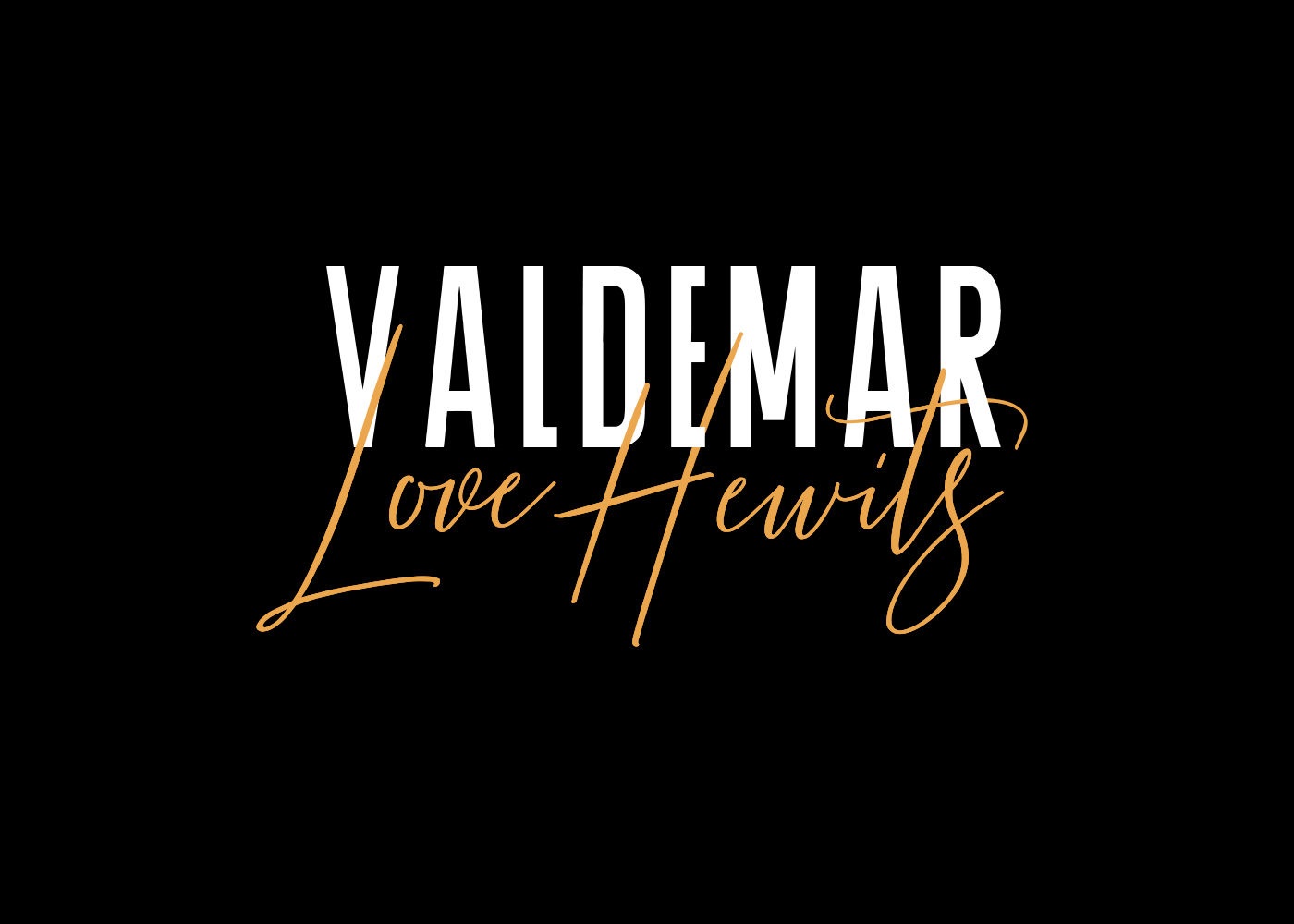
Các phông chữ Love Rosnita sẽ tạo cảm giác bồng bềnh và trôi chảy. Với phông chữ thư pháp này, các bạn sẽ nhận được một script thanh lịch, đẹp mắt với font chữ sans-serif. Love Rosnita font sẽ giúp các thiết kế của bạn có một cái nhìn độc đáo, phù hợp và đặc biệt. Love Rosnita font có thể sử dụng như một chữ ký hoặc font chữ nhấn calligraphy, cũng như một font thư pháp hiện đại dùng để trích dẫn cho các bài đăng trên Facebook, Instagram, Zalo, Twitter, TikTok, YouTube...
Playlist font
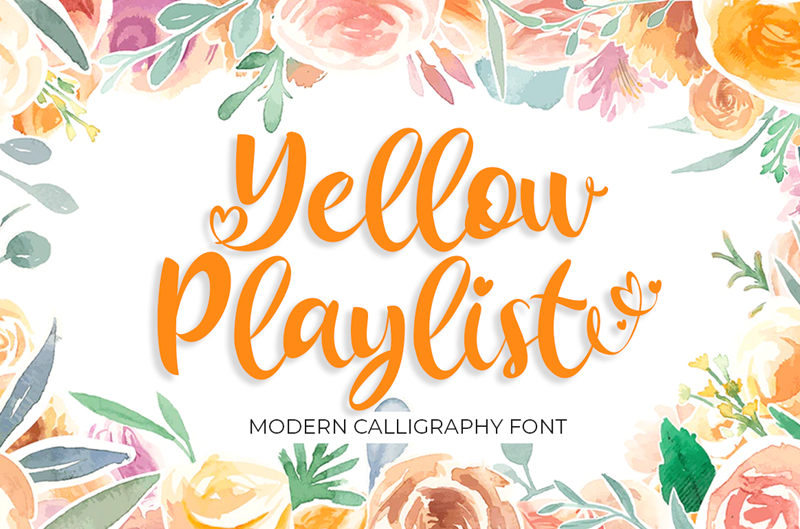
Bạn hãy thử cân nhắc font chữ thư pháp online Playlist nếu bạn muốn một chút đa dạng trong thiết kế của mình. Các bạn có thể tham khảo 3 kiểu phông chữ bao gồm script, trang trí và chữ in hoa, các bạn cũng có thể tham khảo trộn và kết hợp để tạo ra một thiết kế độc đáo. Playlist font có thể được sử dụng trong cả các dự án cá nhân và thương mại.
Mustache brush script font (Envato Elements)
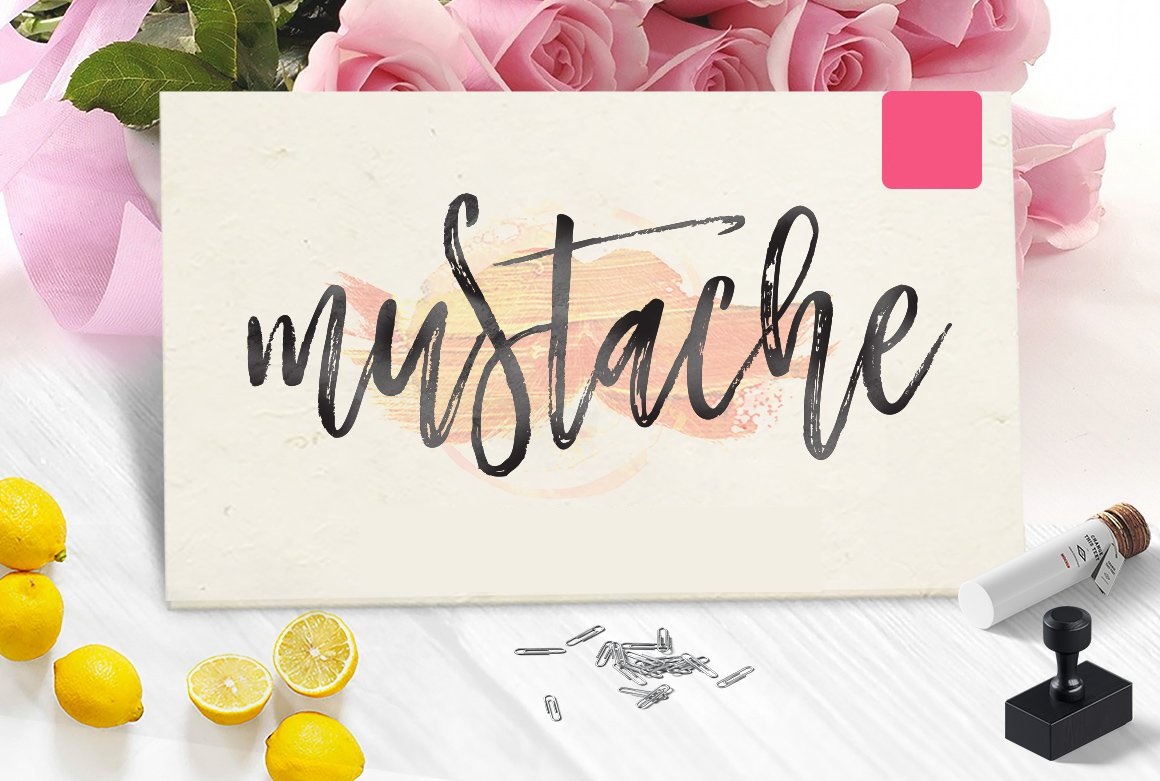
Nếu bạn đang tìm kiếm một font thư pháp bút lông đa năng, hãy chọn Mustache brush script font thử xem nhé. Font chữ Mustache thường gồm có ba kiểu font chữ bao gồm script, nét tròn và mịn. Các bạn có thể "mix & match" những phong cách đó để tạo nên một vẻ ngoài cho chữ viết calligraphy độc đáo nhưng không kém phần hài hòa cho các thiết kế của bạn.
Woodlands font
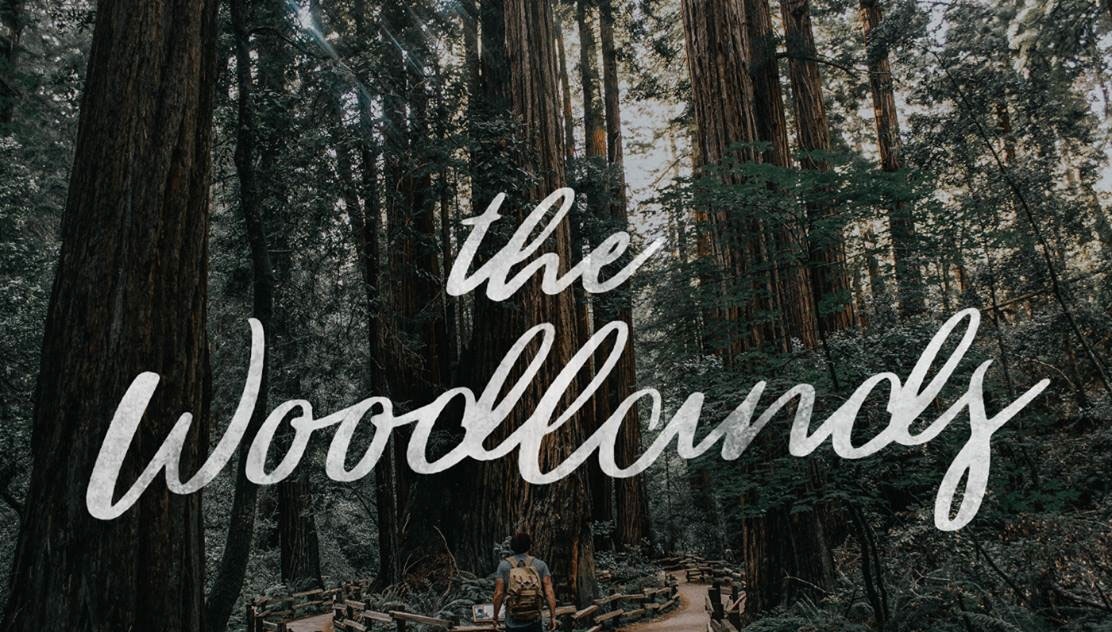
Phông chữ thư pháp Woodlands là một loại modern calligraphy font với cảm giác hơi gồ ghề một chút. Đây là một sự lựa chọn kiểu chữ thư pháp đẹp tuyệt vời cho bất kỳ dự án xây dựng thương hiệu nào liên quan đến các sản phẩm ngoài trời hoặc thiên nhiên. Các bạn có thể sử dụng và tải font chữ thư pháp miễn phí cho mục đích cá nhân và thương mại.
Anjani script modern calligraphy font (Envato Elements)
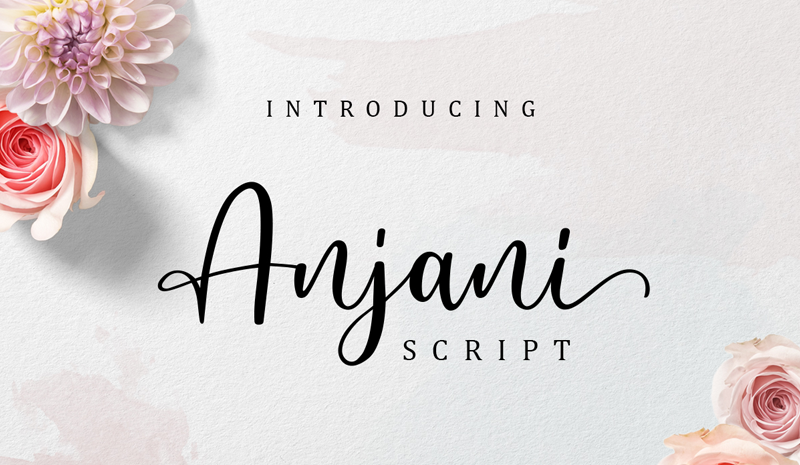
Font chữ Anjani là loại font chữ mà các bạn có thể tải font chữ thư pháp cho photoshop. Anjani script modern calligraphy font mang một vẻ ngoài hiện đại và lãng mạn, vì vậy đây là một sự lựa chọn tốt cho các dự án viết calligraphy thiệp đám cưới, logo, thiết kế áo phông và tiêu đề thư.
Fabfelt script font
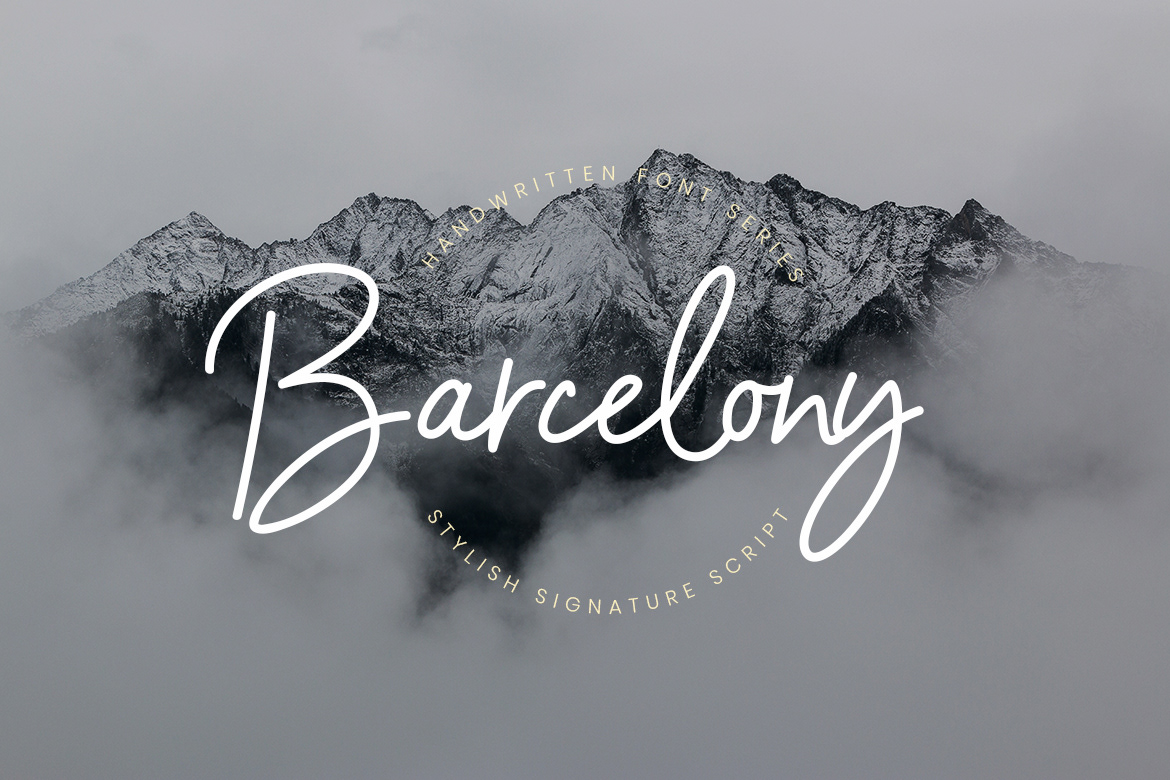
Các bạn hãy thử Fabfelt script font nếu muốn mang đến cái nhìn cổ điển cho thư pháp calligraphy. Font chữ này có các ký tự gọn gàng và được thiết kế bởi Despinoy Fabien. Các bạn có thể sử dụng bộ font chữ này cho mục đích cá nhân và thương mại. Bạn có thể tải font chữ thư pháp cho Android miễn phí luôn nhé.
Everything calligraphy font (Envato Elements)
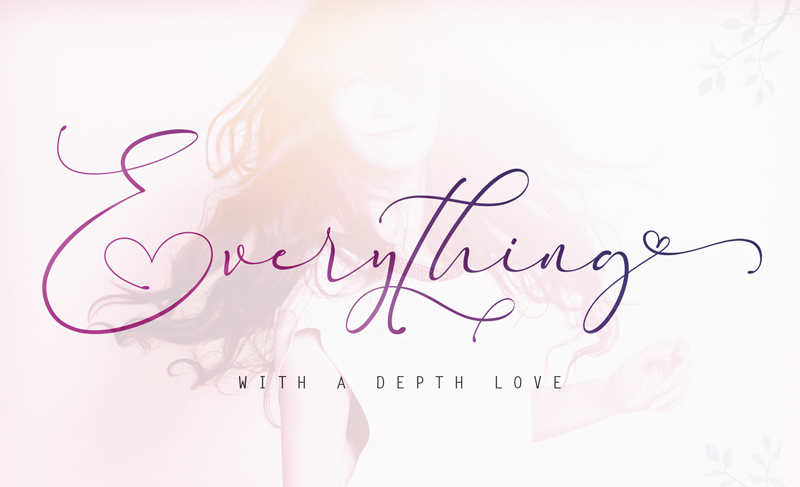
Everything calligraphy font sở hữu các đường baseline lên xuống khác nhau, giúp mang lại cảm giác bồng bềnh và vui tươi cho tác phẩm thư pháp hiện đại của bạn. Đây là một sự lựa chọn thanh lịch và sang trọng cho các mẫu thiệp cưới hay thiệp mời dự tiệc phong cách thư pháp hiện đại.
Naira script font
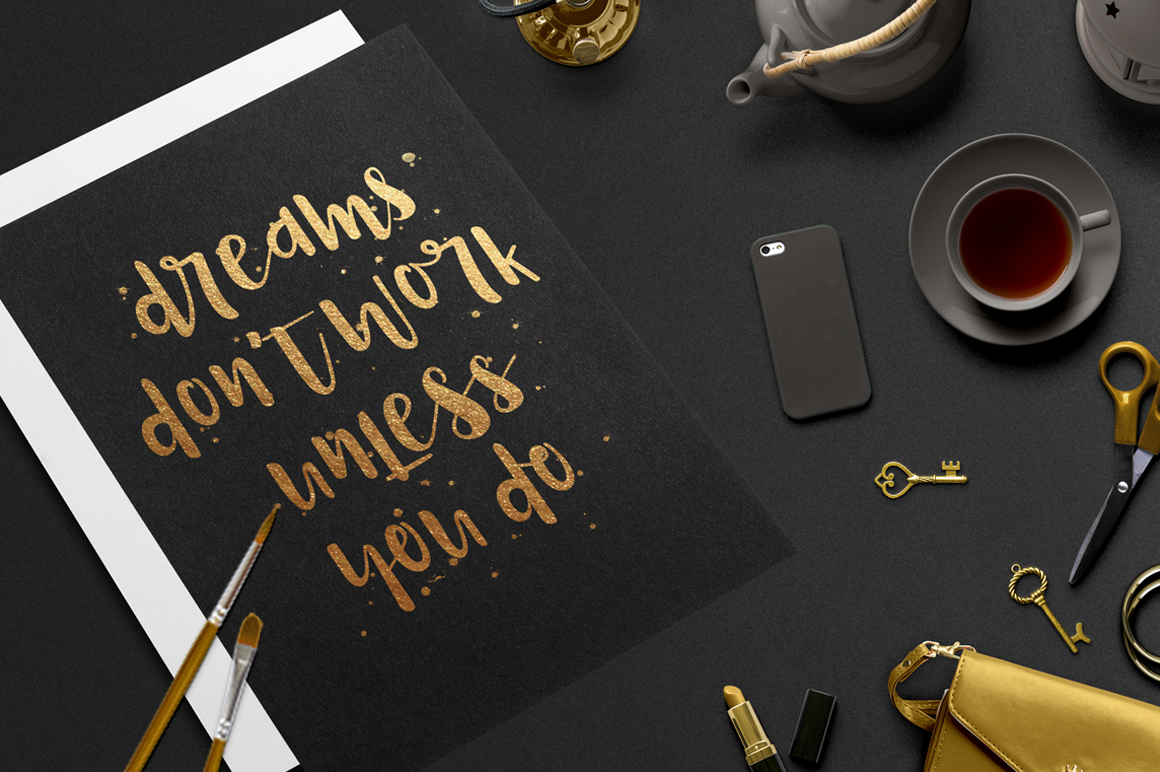
Naira script font là một loại font chữ có các nét đậm và rất nhiều ký tự thay thế để bạn thêm vào thiết kế thư pháp của mình. Naira script font cực kỳ lý tưởng cho các nghệ sĩ muốn xây dựng thương hiệu hoặc làm cho các bài đăng truyền thông trên các trang mạng xã hội.
Billowing script font (Envato Elements)
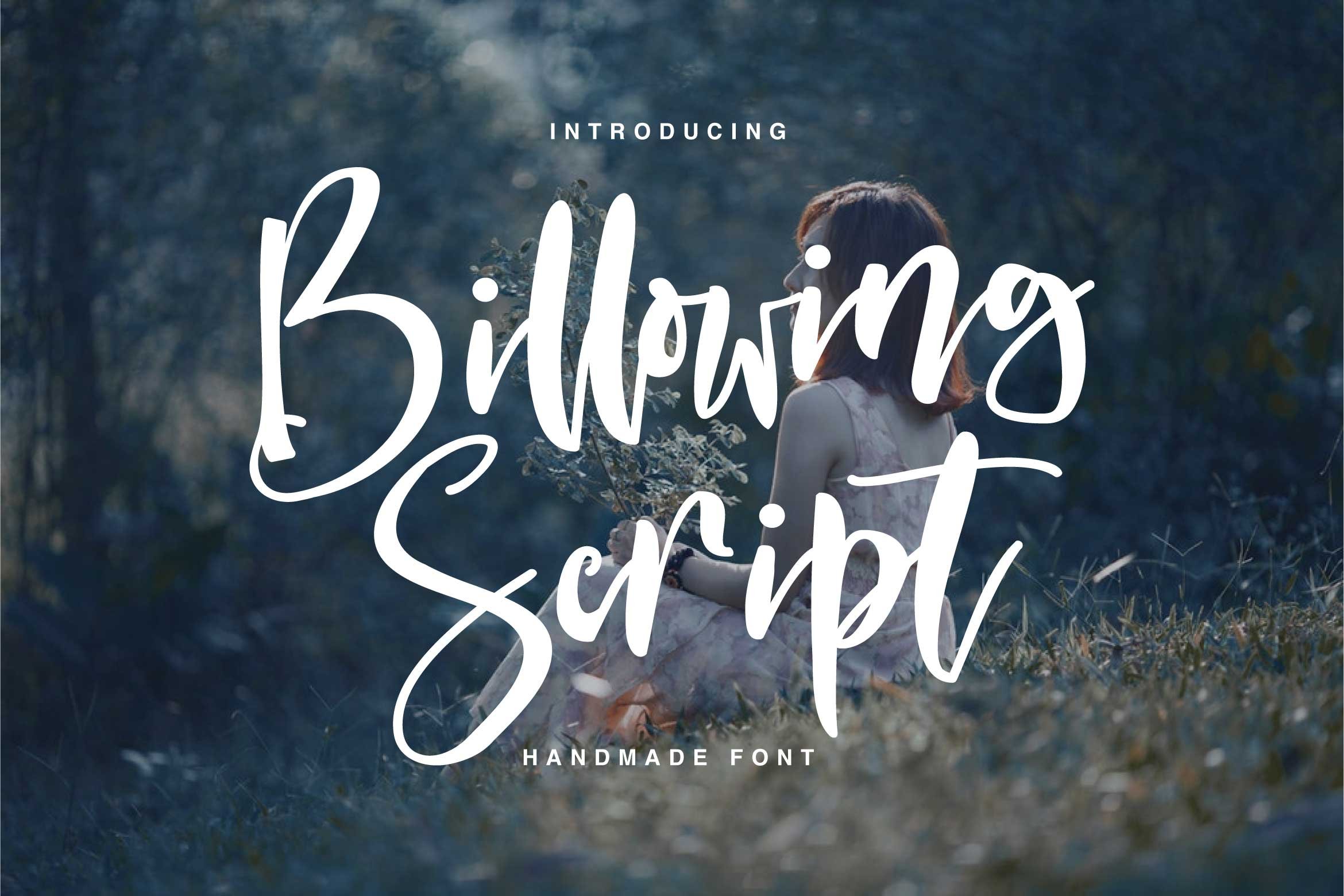
Billowing script font là một font chữ calligraphy hiện đại được lấy cảm hứng từ thiên nhiên. Billowing mang đến cảm giác khá vui tươi, nhẹ nhàng và thanh lịch hơn. Billowing sở hữu 243 glyphs và 64 ký tự thay thế cách điệu, đường nối tiêu chuẩn và các tính năng OpenType khác mà bạn có thể lựa chọn.
Endestry modern calligraphy font
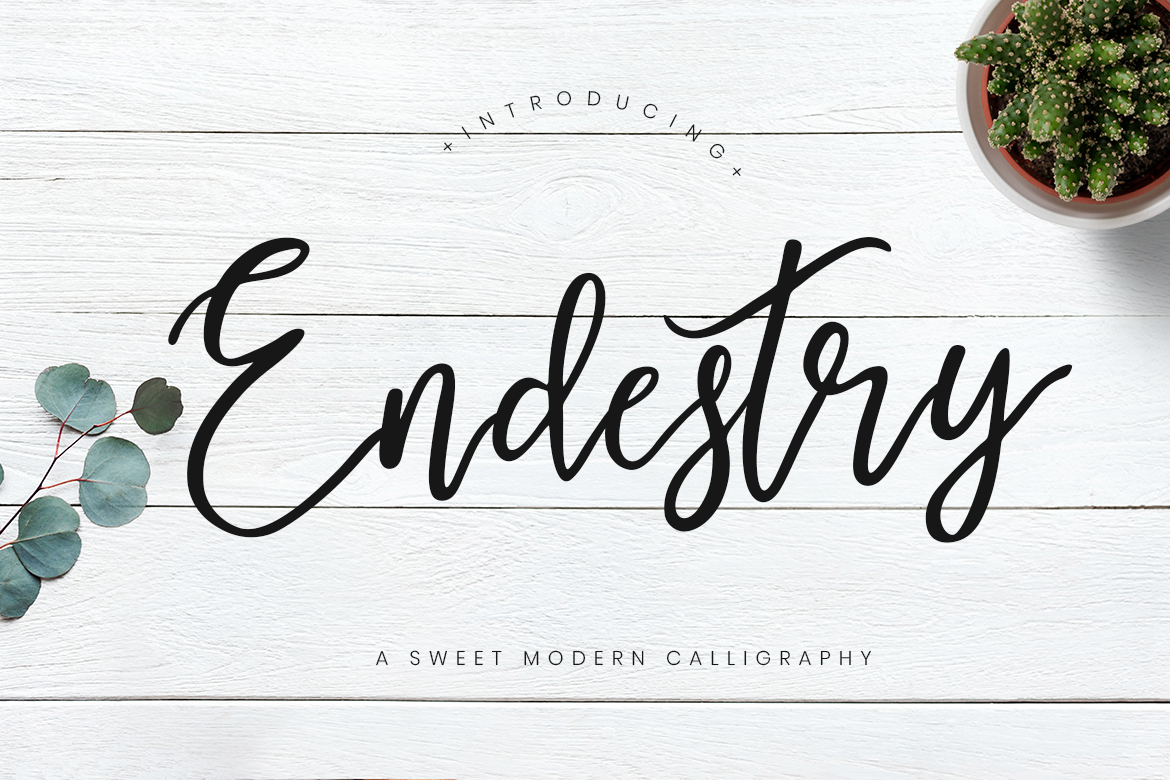
Endestry modern calligraphy font được thiết kế bởi Studio Creatype với những nét uốn lượn tuyệt vời. Đây là một sự lựa chọn hoàn hảo nếu bạn đang muốn thiết kế logo và các dự án xây dựng thương hiệu cũng như tiêu đề thư, thư mời, bài đăng trên phương tiện truyền thông xã hội theo dạng thư pháp modern calligraphy.